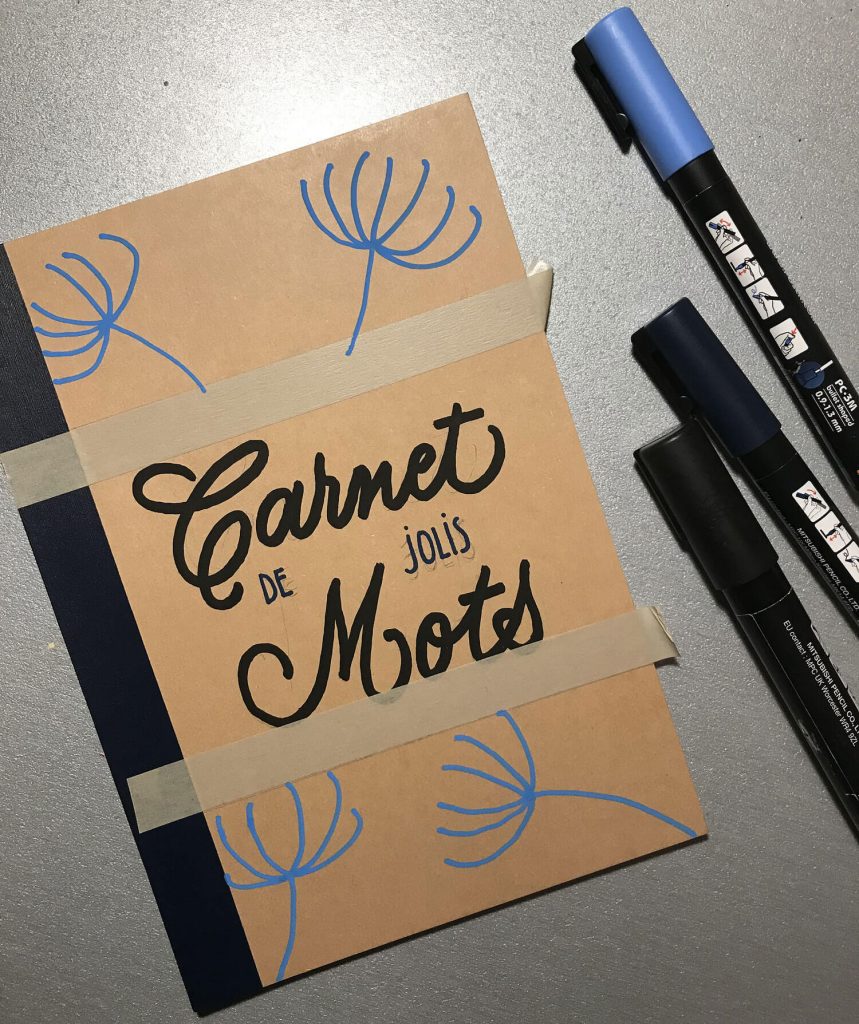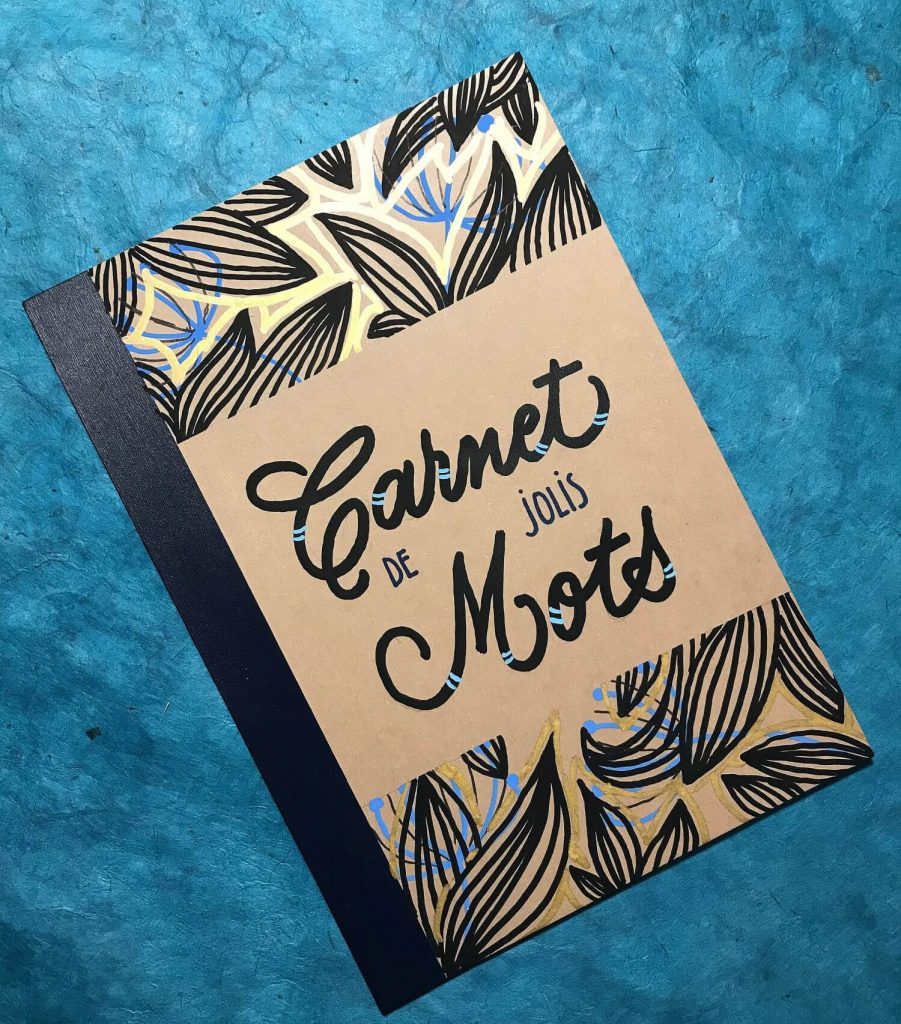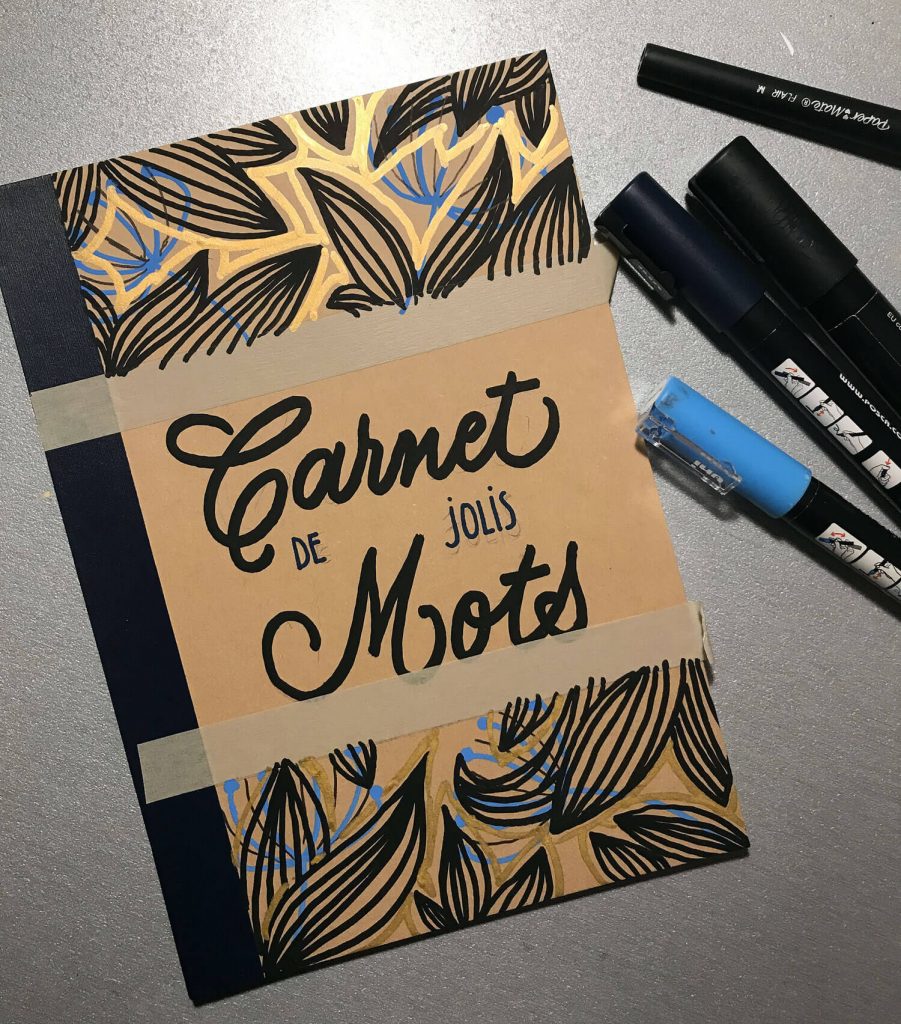
Pas de blabla aujourd’hui, juste une idée de DIY pour personnaliser un carnet. Ici, j’ai travaillé sur un petit carnet de citations, car j’en ai sur des bouts de papiers, dans divers carnets de notes, bref, partout.
C’est la nième fois que je le tente : rassembler les citations qui me plaisent en un seul et même carnet !
Pour ce faire, rien de bien méchant côté matériel. Il faut :
• Un carnet : j’ai pris un format A5, trouvé chez Muji à un prix défiant toute concurrence
• Des poscas de différentes couleurs
• Du Masking Tape, ou du ruban de masquage
• Crayon de papier, gomme, règle
Les idées et les pistes
• L’idée N°1 c’est « ras le bol des couronnes », j’en peux plus, on en voit partout, j’en ai fait dix mille. J’ai donc opté pour un format cadre, d’où la nécessité du masking tape.
• L’idée N°2 c’est « du végétal oui, mais graphique ». Donc pas de petites fleu-fleurs pour cette fois-ci !
• L’idée N°3 c’est « plutôt moderne, esprit années 30 », ce qui a motivé le choix de couleurs et la touche de doré
Pour le lettrage, je suis dans l’esprit de la plume palette, mais réalisé avec un posca pour éviter les grosses bavures d’encre potentielles.
Comment faire ?
On commence par le lettrage que l’on aura bien centré, et préalablement écrit au crayon de papier. Pour ne pas avoir de traits de crayon, je gomme légèrement avec une gomme mie de pain pour conserver juste ce qu’il faut pour me repérer.
Ensuite, on dispose le masking tape pour délimiter la zone à décorer. Rien de plus simple! Pour les motifs, vous pouvez vous faire un brouillon au préalable. Là j’y suis allée franco, sans filet, en dessinant d’abord les formes de base. Vous reconnaîtrez les inspirations du défis 100 fleurs
Pour que l’ensemble « fonctionne », vous comprenez qu’il faut que cette zone de motifs soit assez fournie, pour créer du contraste. Le masking tape vous garantit des lignes bien droites et bien nettes.
D’ailleurs, hop ! On l’enlève délicatement et… tada !!
Comme le lettrage faisait un peu « nu », j’ai rajouté des petits traits, comme des petits liens ou des élastiques.
Pour que votre compo fonctionne, quelques astuces
• Il faut que le motif soit fourni et contrasté
• Il faut que le texte soit aéré
• Il ne faut pas hésiter à décentrer les motifs : ici aucune feuille est entière par exemple, elles semblent toutes émerger des bords.
Vous pouvez tracer une esquisse légère pour vous guider, et l’estomper délicatement à la gomme.
J’espère que ce tuto vous a inspiré.es, pour vos carnets, mais aussi pour des cartes, votre bullet journal  ou des marque-pages. De mon côté, je n’ai plus qu’à reporter mes citations !